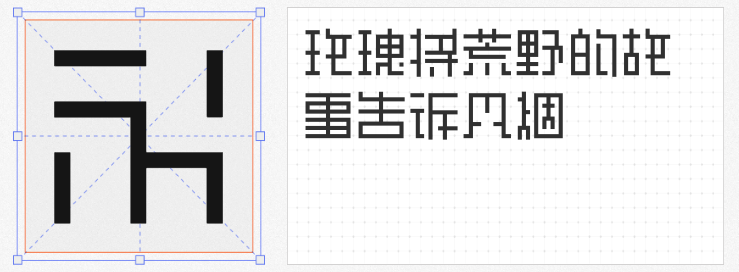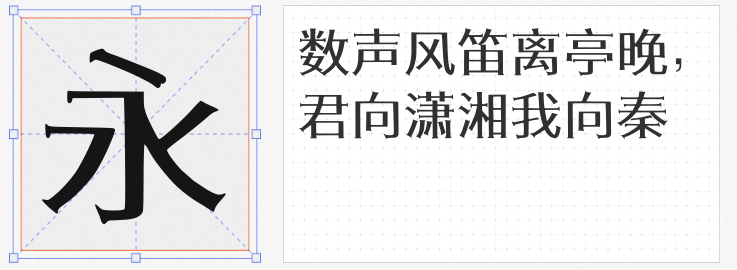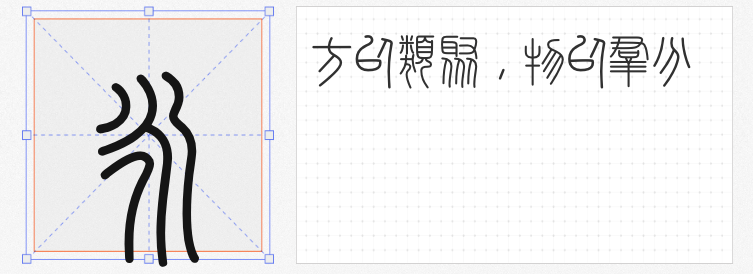
在当代设计语境中,创意字体已成为突破视觉同质化的关键工具。以下四款风格迥异的字体,通过结构解构与文化融合,为品牌叙事与视觉传达开辟了全新维度。
作为类像素体代表,该字体以方格矩阵重构笔画形态,通过像素颗粒的疏密排列形成独特的机械质感。其设计语言既保留了早期电子屏幕的复古基因,又通过现代排版技术优化了阅读流畅性。这种虚实交织的视觉效果,使其在科技主题海报、游戏界面及数字艺术装置中,能精准传递未来感与怀旧情绪的碰撞。
基于日本「解星计划」的衍生创作,该字体以传承字形检校表为基准,通过繁简体字与注音符号的补全,构建出跨文化书写的完整体系。其笔画设计融合了东亚传统书法的起承转合与现代几何的理性切割,形成既保留文化基因又具国际视野的独特风格。这种兼容并蓄的特性,使其在文化交流项目、多语言出版物及全球化品牌视觉中,能实现传统与现代的对话。
以宋体为蓝本的创新演绎,该字体通过棱角分明的笔画与筋骨内蕴的结构,构建出“一诺千金”的视觉宣言。其设计既延续了宋体的文化厚重感,又通过锐利转折赋予现代商业所需的坚定气质。这种刚柔并济的美学特征,使其在餐饮品牌塑造、文化展览视觉及企业形象系统中,能同时传递传统匠心与当代态度。
源自大学生科技创新项目的篆书字体,以峄山石刻为灵感源泉,通过数字化技术复现了秦篆的典雅风韵。其笔画圆润流畅,结构对称均衡,既保留了金石篆刻的古朴质感,又通过现代字库技术优化了实用性能。这种历史文脉与数字技术的融合,使其在文化IP开发、传统艺术展览及高端品牌包装中,能成为连接古今的文化符号。
四款字体通过技术革新与文化转译,展现了创意字体从工具属性到文化载体的进化轨迹。无论是追求科技感、跨文化表达,还是传统美学复兴,这些作品都为设计师提供了突破常规的视觉解决方案。